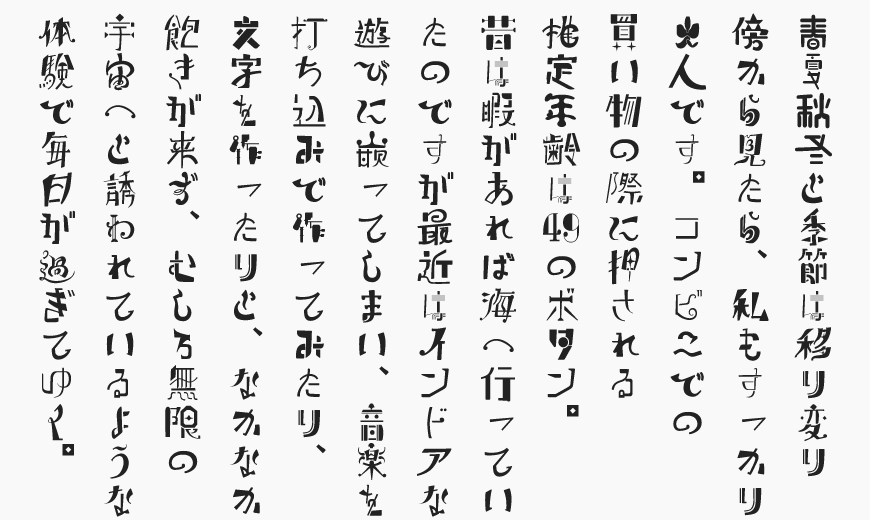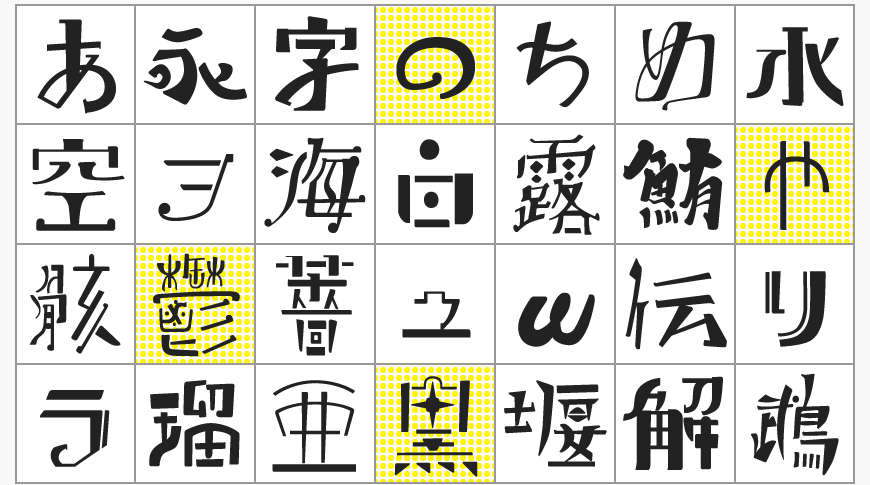
ピグモ 01
ピグモ01(Pigmo 01)是一款基于 ピグモ00(Pigmo 00) 扩展开发的免费可商用日文字体。字体在原有基础上新增了完整的平假名、片假名、英文字母、数字及更多汉字字符,并进一步完善字符集,使其既保留了手写字体自由随性的艺术气质,又具备更加完整的实际应用能力,是一款兼具实验性与实用性的创意展示字体。
从整体设计来看,ピグモ01 并未遵循传统印刷字体严谨统一的造字规范,而是刻意保留了大量手工绘制的痕迹。字体线条粗细变化明显,笔画边缘略带不规则起伏,转折、收笔和连接位置都具有自然书写感,使每个字符都呈现出鲜明的个性。这种略带稚拙却富有设计感的表现方式,使字体拥有强烈的人文气息,也让排版更加生动有趣。
从图片展示可以看到,字体采用纵向排版时依然保持较高的辨识度。虽然每个字形都存在不同程度的造型变化,但整体重心稳定,字面大小控制统一,在连续阅读时不会产生明显的视觉跳跃。这说明设计者在追求手绘风格的同时,对字体的整体节奏进行了细致调整,使其兼顾艺术表现力与阅读体验。
在字形细节方面,ピグモ01 大量融入了书法、漫画字体以及装饰字体的设计语言。部分笔画采用夸张的弧线、折角、留白及镂空处理,某些字符甚至突破传统结构比例,通过局部夸张强化视觉记忆点。例如图片中的部分汉字采用粗细交替的笔画设计,而假名则保持更加轻松灵活的书写节奏,两者共同构成极具日系创作风格的视觉语言。
字符集也是这款字体的重要优势。相比早期版本,ピグモ01 新增了平假名、片假名、全角与半角英数字,同时扩展支持希腊字母、西里尔字母以及 JIS 第一、第二水准汉字,整体字符数量达到六千余汉字,可满足绝大多数日文设计及多语言排版需求,在海报、封面、漫画、游戏界面以及文化创意设计中都具有较高的实用价值。
作为一款展示型字体,ピグモ01 更适用于标题、品牌视觉、包装设计、插画配字、杂志封面、文创产品、独立出版物以及各类需要强化个性的设计项目。当应用于较大字号时,丰富的笔画变化能够充分展现字体的艺术特色;搭配简洁版式使用,也能够形成鲜明的视觉层次与品牌辨识度。